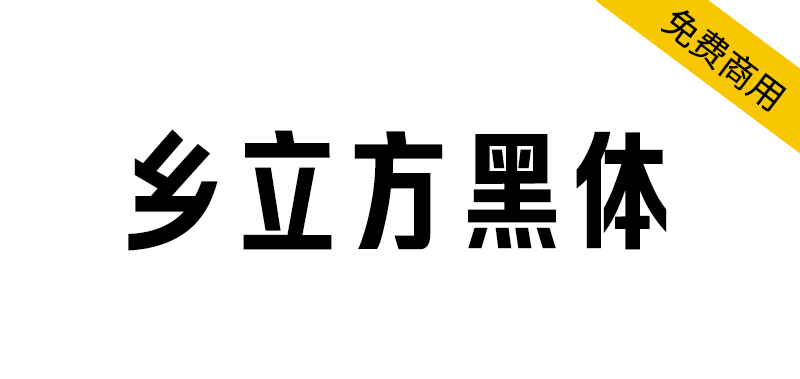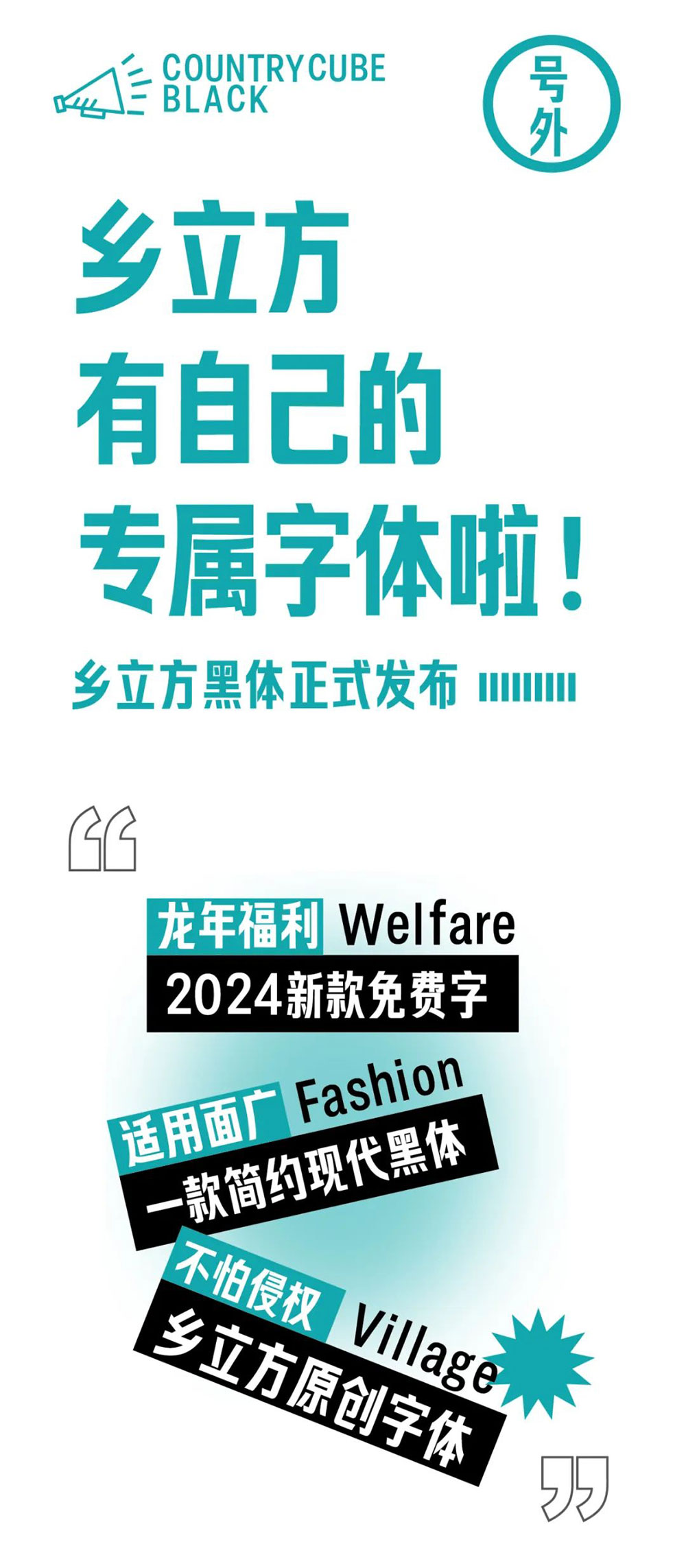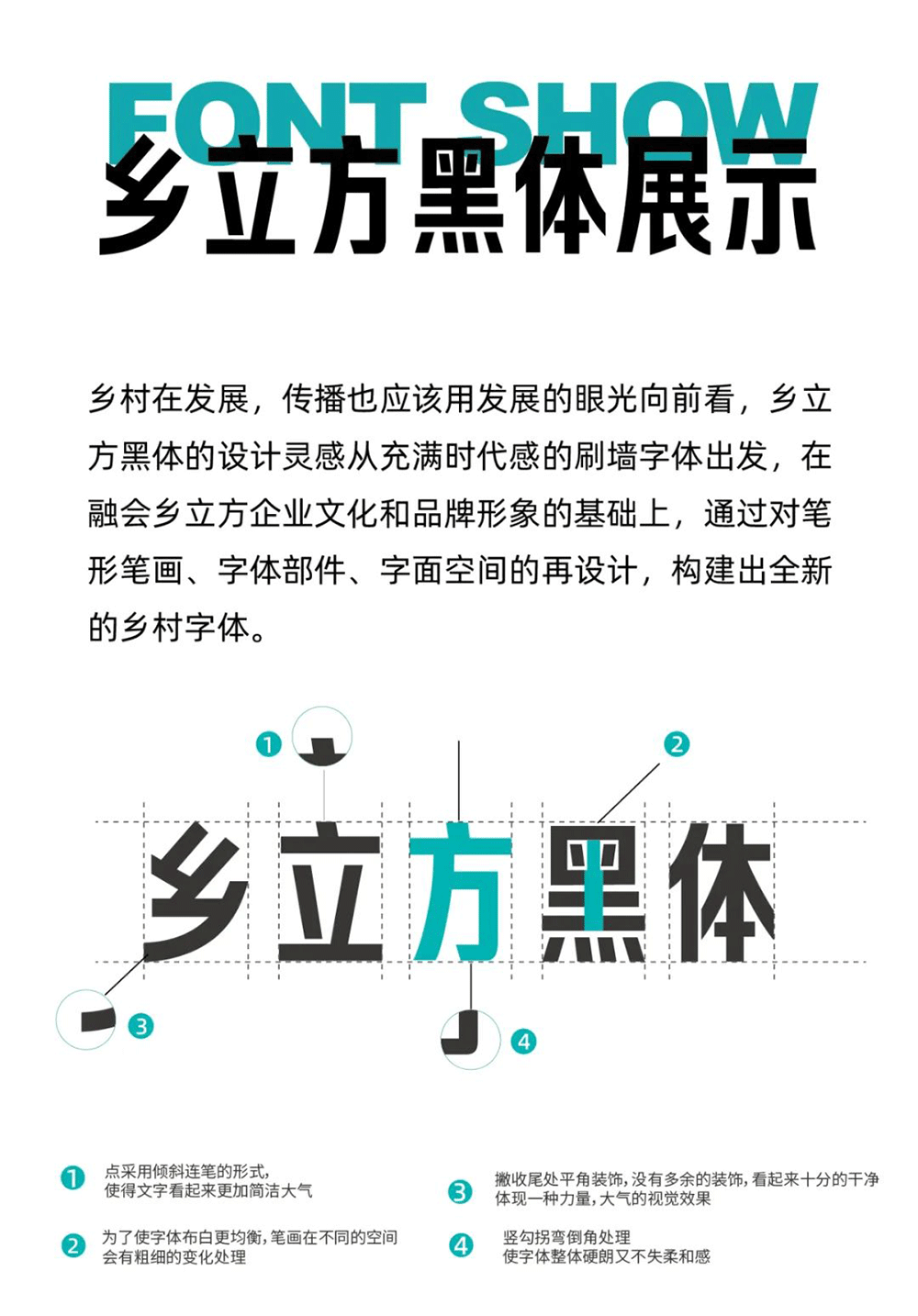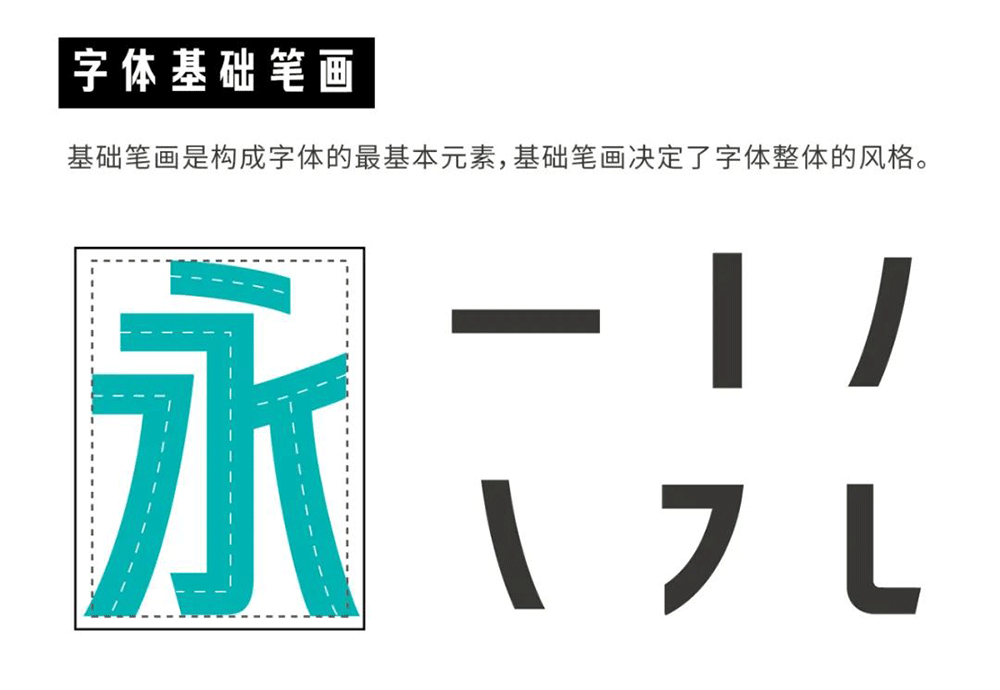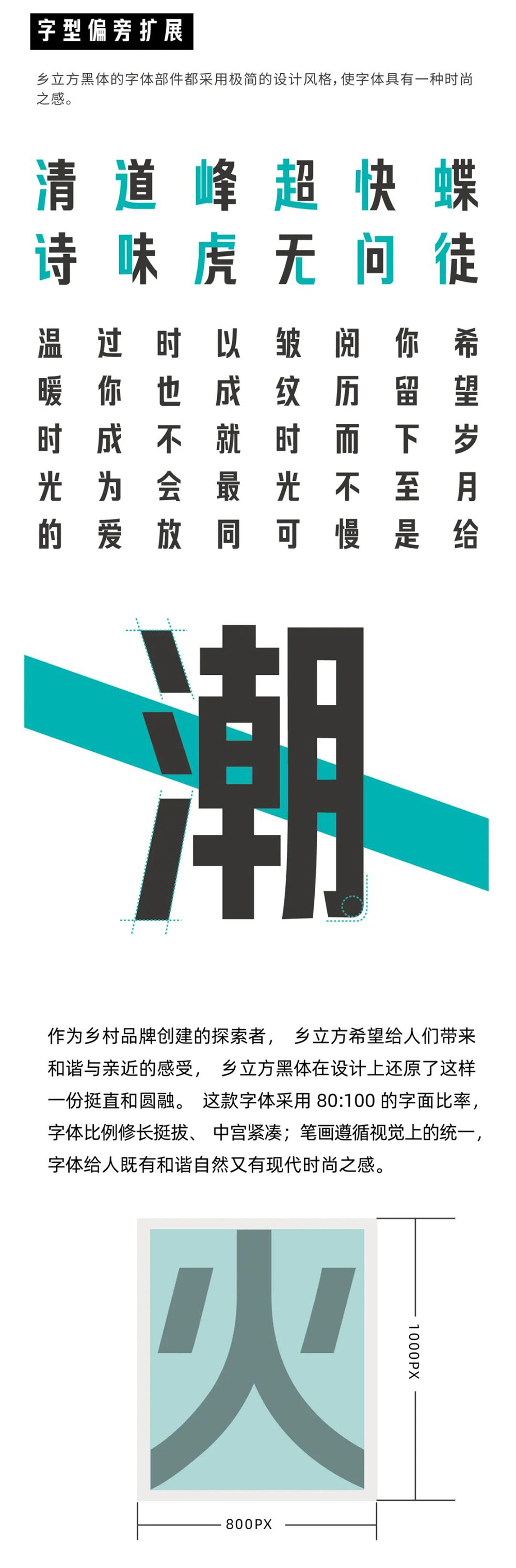
我是乡立方黑体,由火石品牌字体团队为乡立方量身定制,以字为媒,绘乡村风情,传品牌温度。
乡立方字体设计团队秉承服务大众的原则,致力于打造一款既实用又广泛适用的字体,希望它能被广泛应用于各行各业,真正做到字体好用,适用面广,实现字体使用便捷、应用场景丰富多样,无论在哪种传播媒介中都能展现出卓越的效果。
乡立方黑体总共囊括了4500个基础常用字,可覆盖日常98%的使用范围,未来,我们将根据实际情况逐步补充和完善字库。